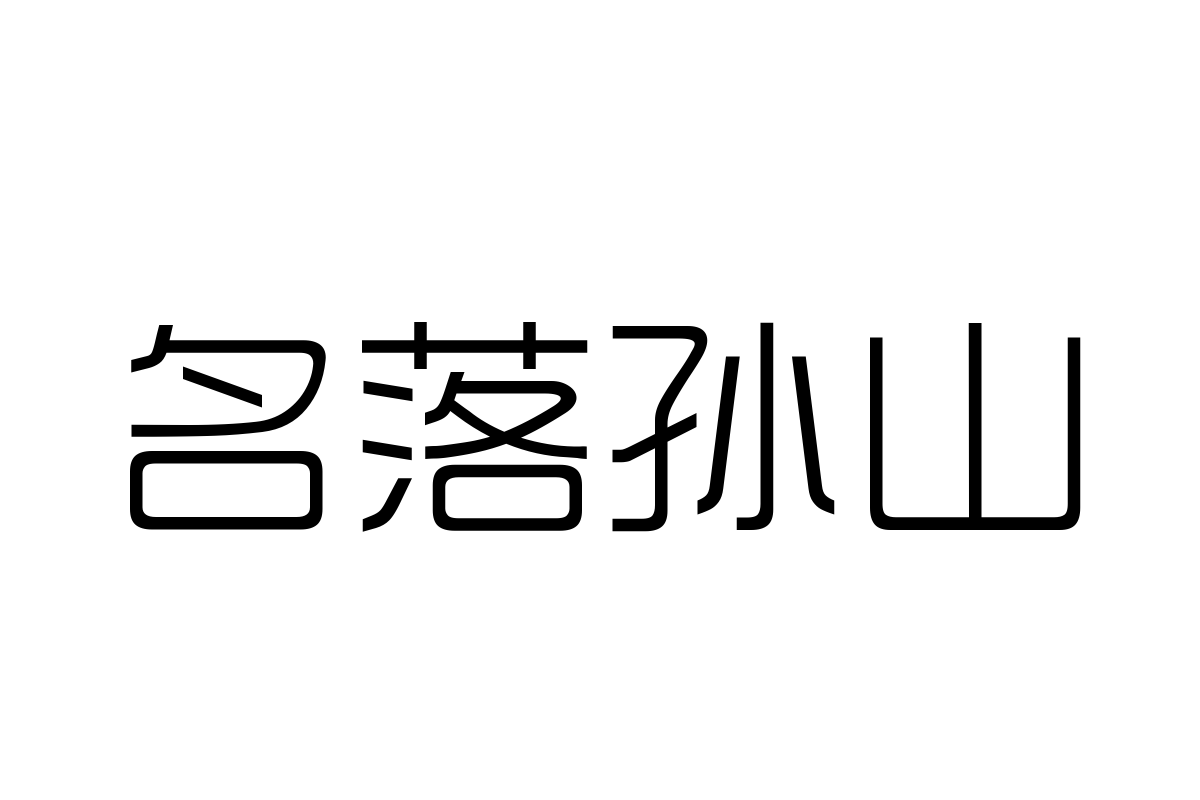
三极时尚韵黑字体是一款现代感强烈的无衬线字体,适用于各种商业和专业场合。这款字体以其简洁、清晰的特点,能够有效地传达信息和增强视觉效果。
该字体具有以下特点:
– 简洁的线条设计,易于阅读和理解
– 适合用于标题、标志、广告等需要突出显示的部分
– 在不同大小和排版下,都能保持良好的可读性
– 适用于各种背景颜色,包括深色和浅色
总之,三极时尚韵黑字体是一款非常实用且美观的字体,适合用于需要强调信息传递的商业和专业场合。